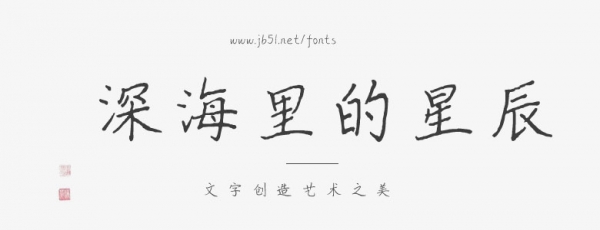
深海里的星辰是一款非常漂亮的中文字體,同時(shí)也是由文道字庫(kù)傾情發(fā)布的作品,字體字型規(guī)中規(guī)矩,凸顯其獨(dú)特的楷書魅力,整體效果十分的賞心悅目,適應(yīng)于報(bào)紙和雜志和書籍中常用字體海報(bào)、個(gè)性促進(jìn)品牌標(biāo)志設(shè)計(jì)、字體設(shè)計(jì)、文本裝潢、信息展示、篆刻制模英文、數(shù)據(jù)制作、裝潢設(shè)計(jì)、視覺設(shè)計(jì)、字帖等一切合法應(yīng)用場(chǎng)景,有喜歡的朋友可免費(fèi)下載收藏